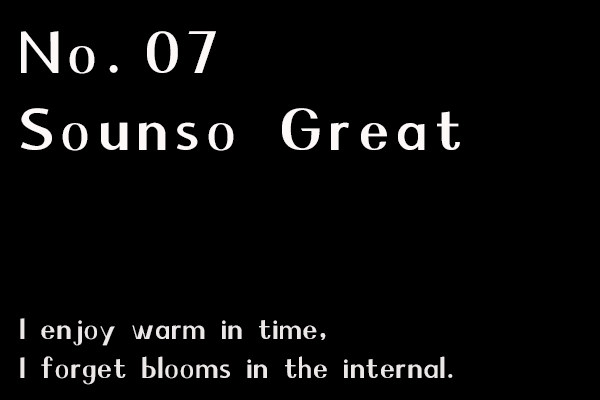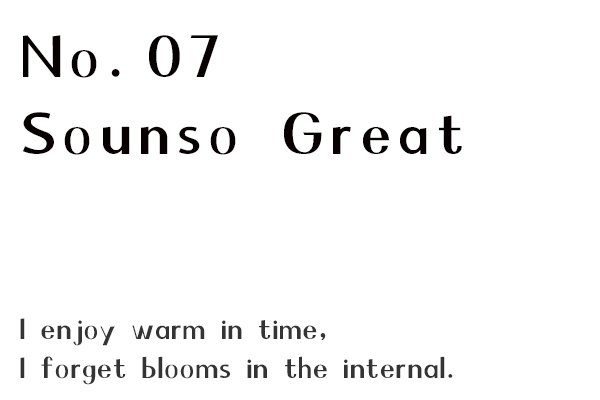
字体方圆结合,粗细变化有致,稳固,流畅精致优雅,适用于搭配标志、广告标语、商业广告等高端属性。购买须知:“下载服务费”与“字体VIP”所获得字体 仅用于个人非商用, 商用请联系付费授权。本字体为电脑用字,手机没有root权限不支持直接手机换字(手机如何root,请自行百度搜索教程)。购买前请先 了解清楚后再付款 ,字体为虚拟产品无法回收 一旦购买不支持退款。